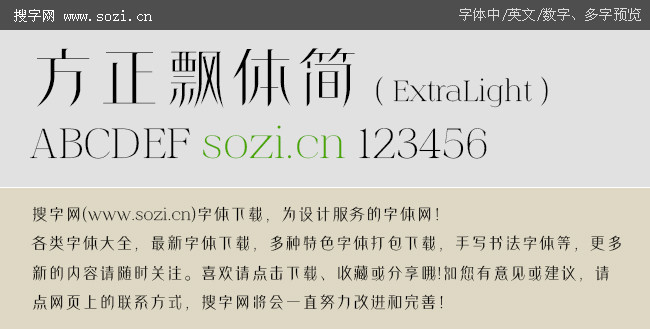
方正飄體簡ExtraLight
搜字網提供一款方正飄體簡中文字體下載,方正飄體系列字取柔美之姿,飄逸之感,適合于追求優雅品格類別的相關標題。于字里行間,求風度之翩翩,展高挑之身姿,顯優雅之品行,有微風緩緩吹來之感。由粗至纖細五款系列,粗體穩重而醒目,細體別致而性感,總之體態各異。適合應用于藝術設計、平面宣傳設計、網頁設計等場合使用。